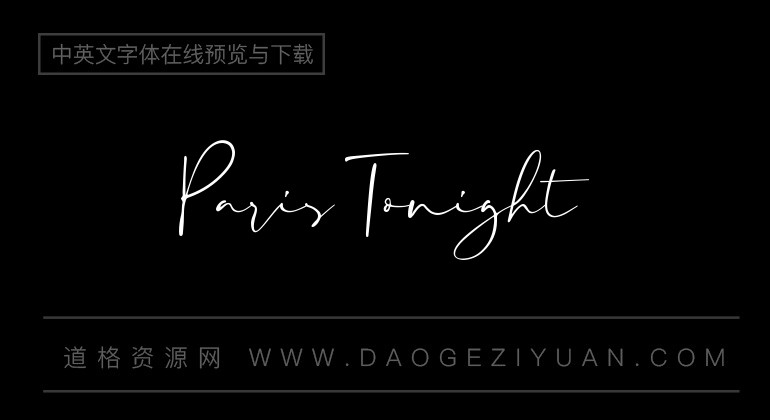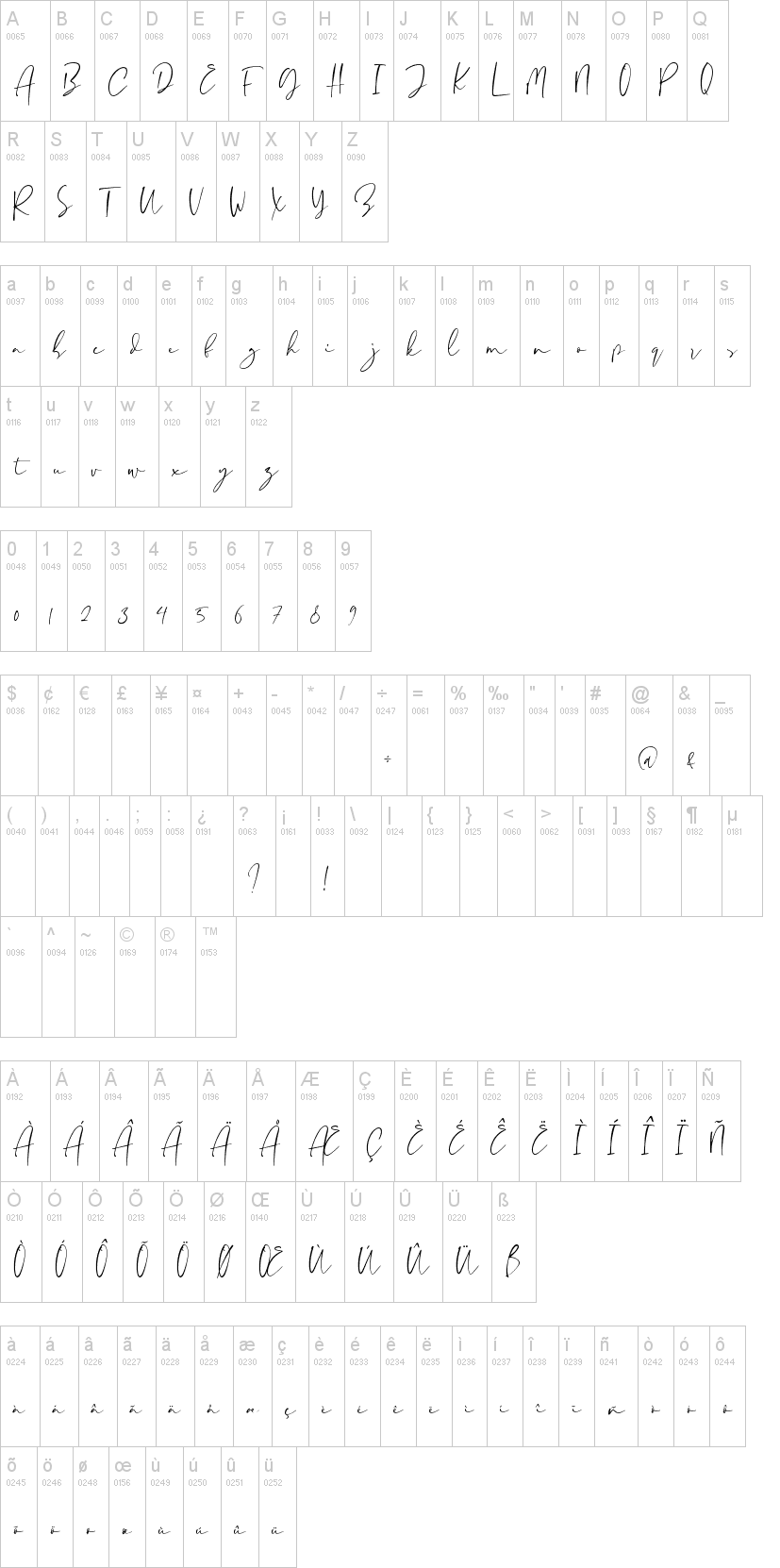
Paris Tonight 是一款具有现代感的英文字体,它具有精致的曲线和清晰的细节,使得字体显得时尚、优雅,是一款非常适合用于海报、海报、宣传物料等的字体。它有大、中、小三种字号,可以满足不同需求,还有多种字形,可以更好地表达设计者的想法。内容介绍
Paris Tonight是一款非常不错的手写艺术字体,具有很好的视觉感,适合于文化类的宣传设计、商业类品牌的广告和产品包装设计以及个性化文字排版等较多场景。